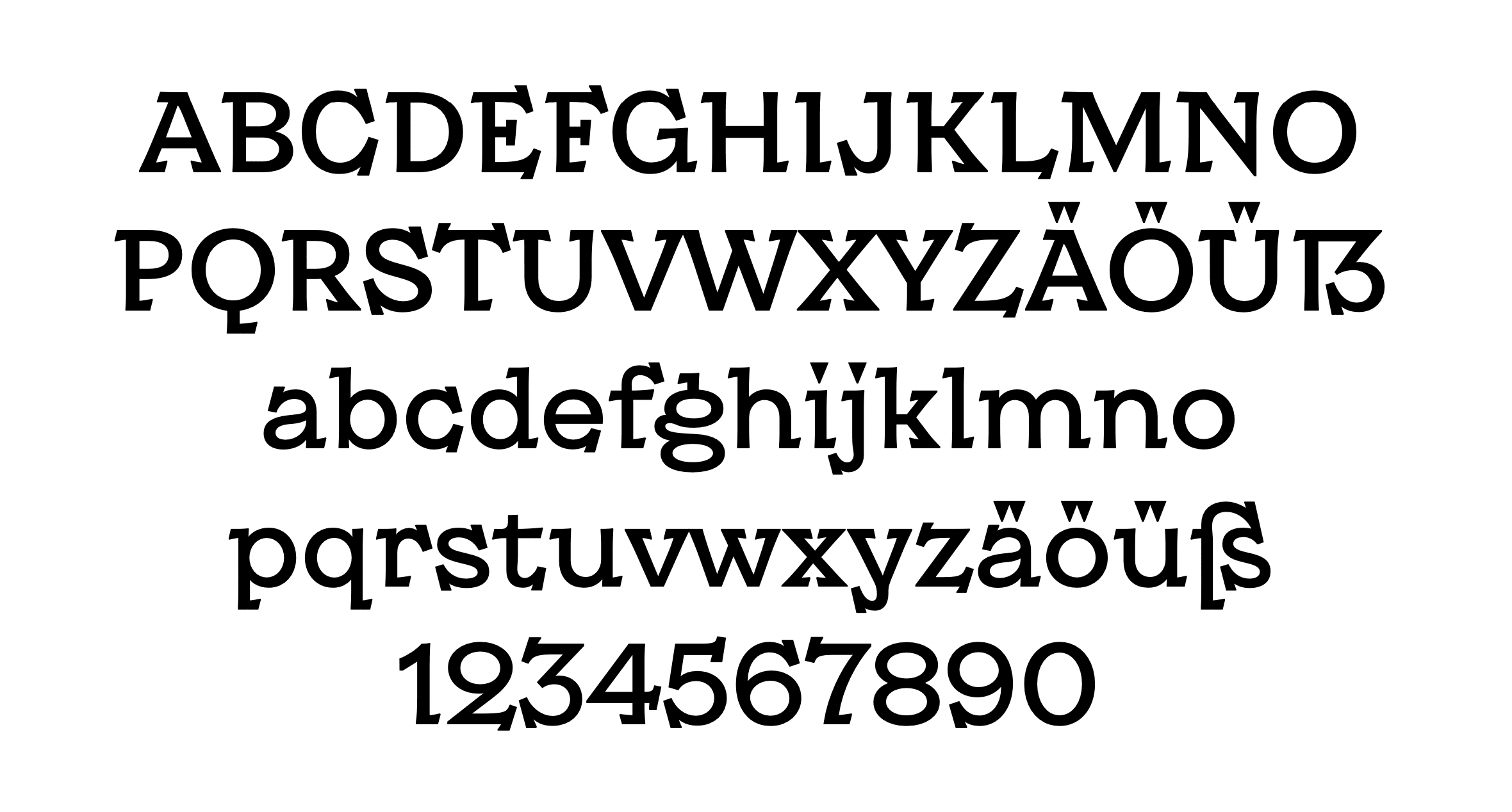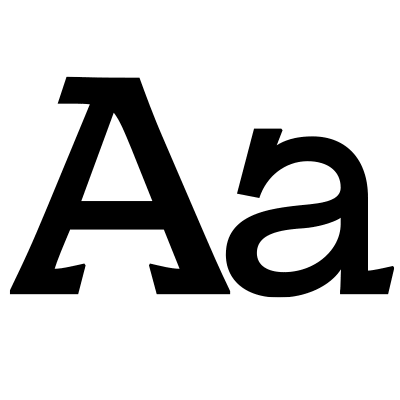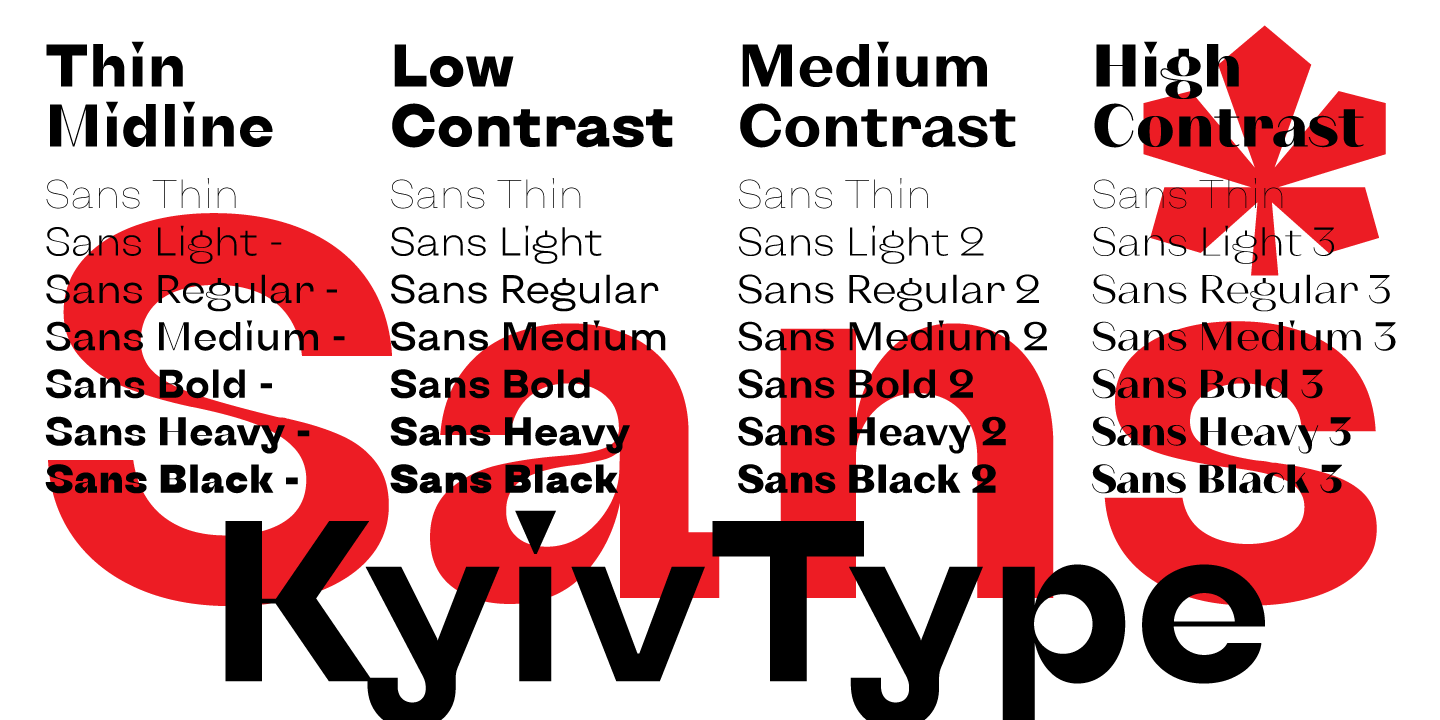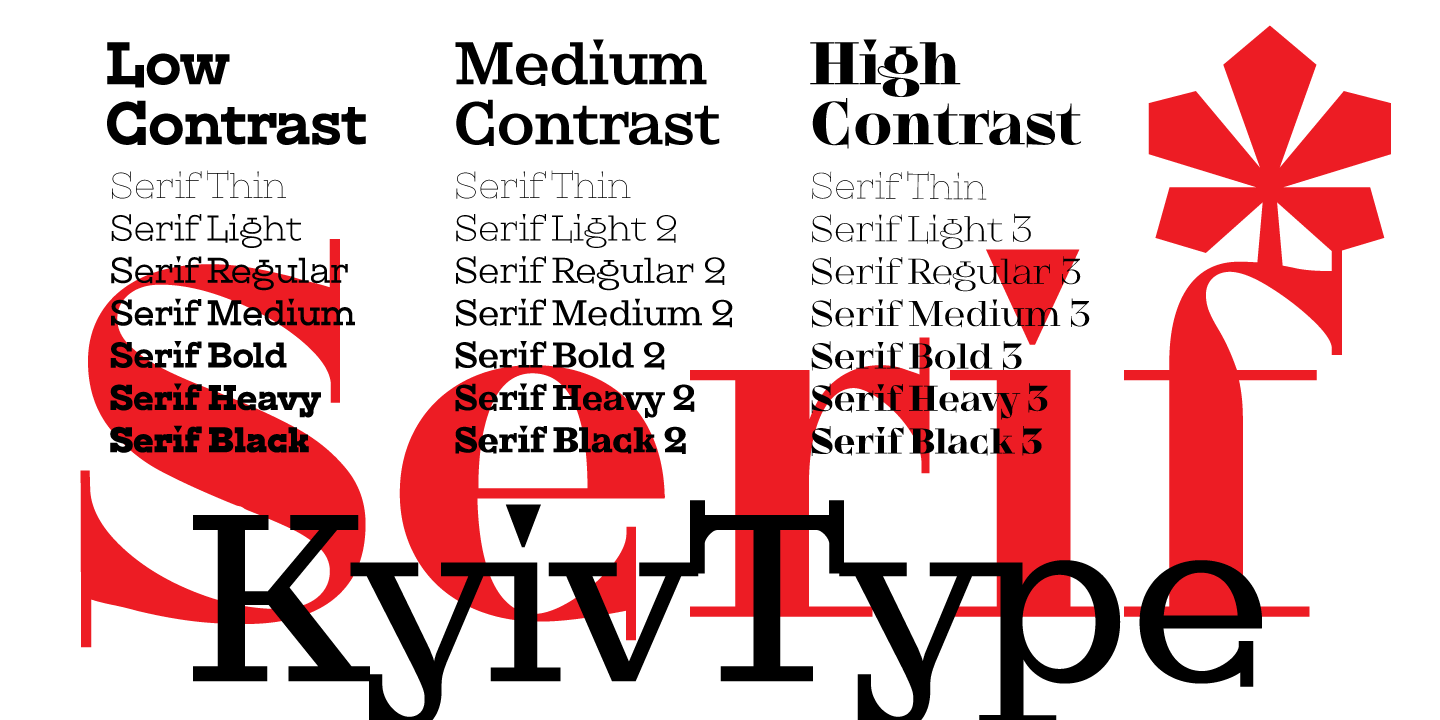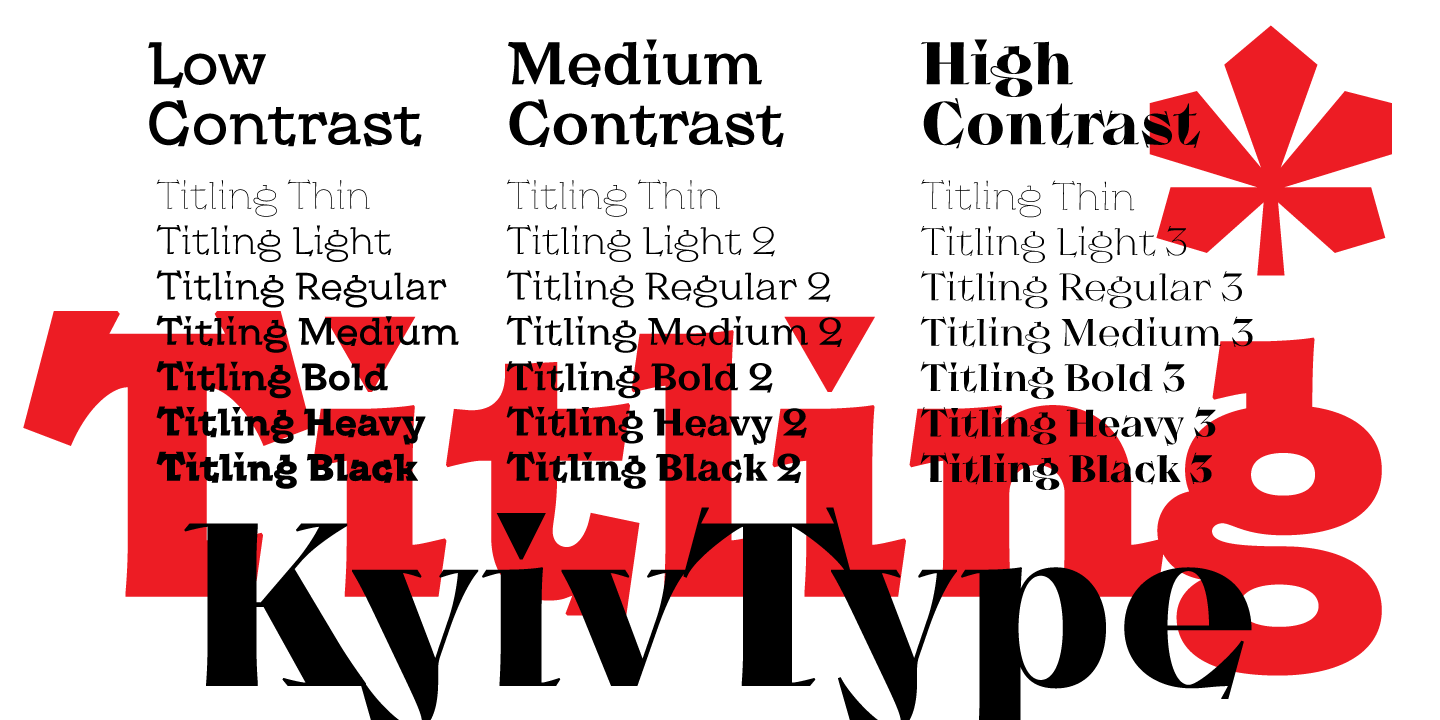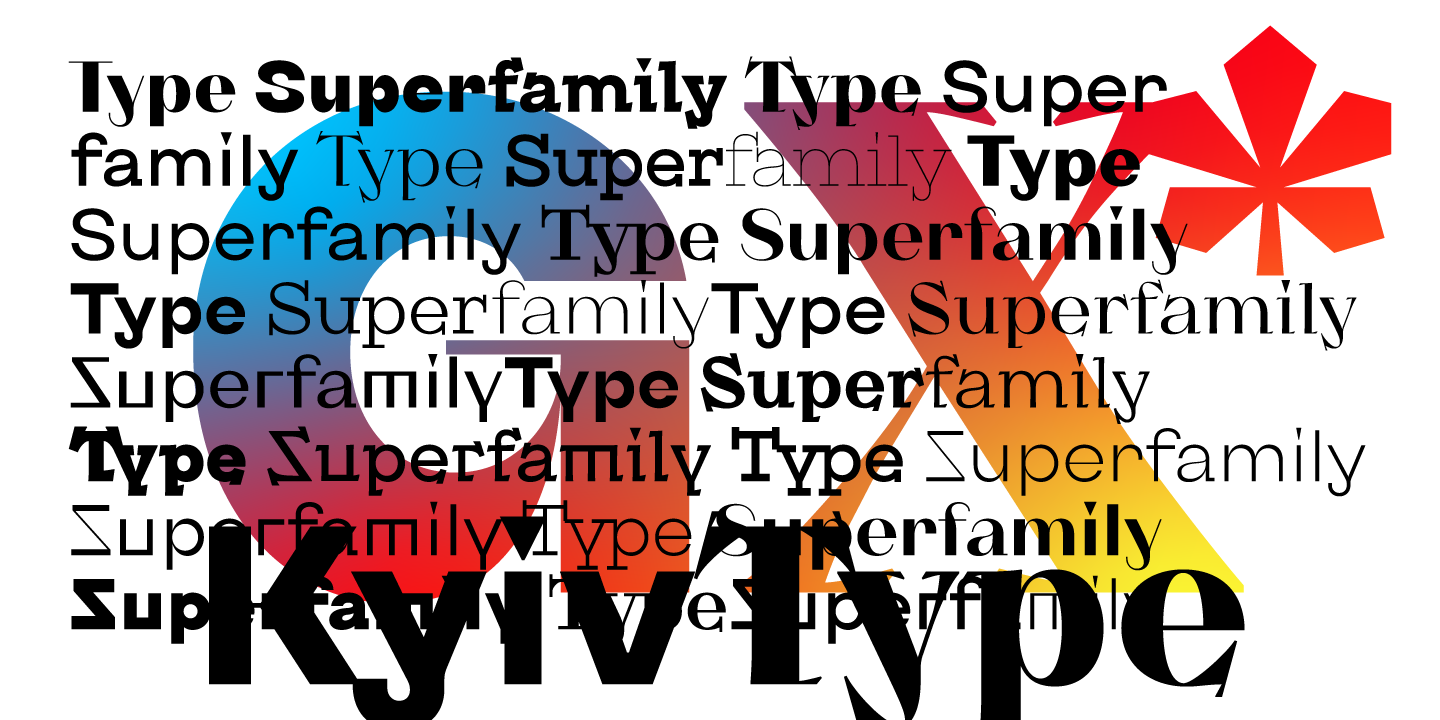
KyivType Superfamily 1.0.0
Eine kostenlose Schriftfamilie mit lateinischer und kyrillischer Belegung von Dmitry Rastvortsev. Wahlweise nutzbar als variabler Font in drei Varianten (Sans, Serif und Titling) oder in 63 aufrechten Einzelschnitten. Ebenfalls im Paket enthalten sind Piktogramme mit Motiven aus der Stadt Kiew von Olya Kiselova.
Dmitry Rastvortsev